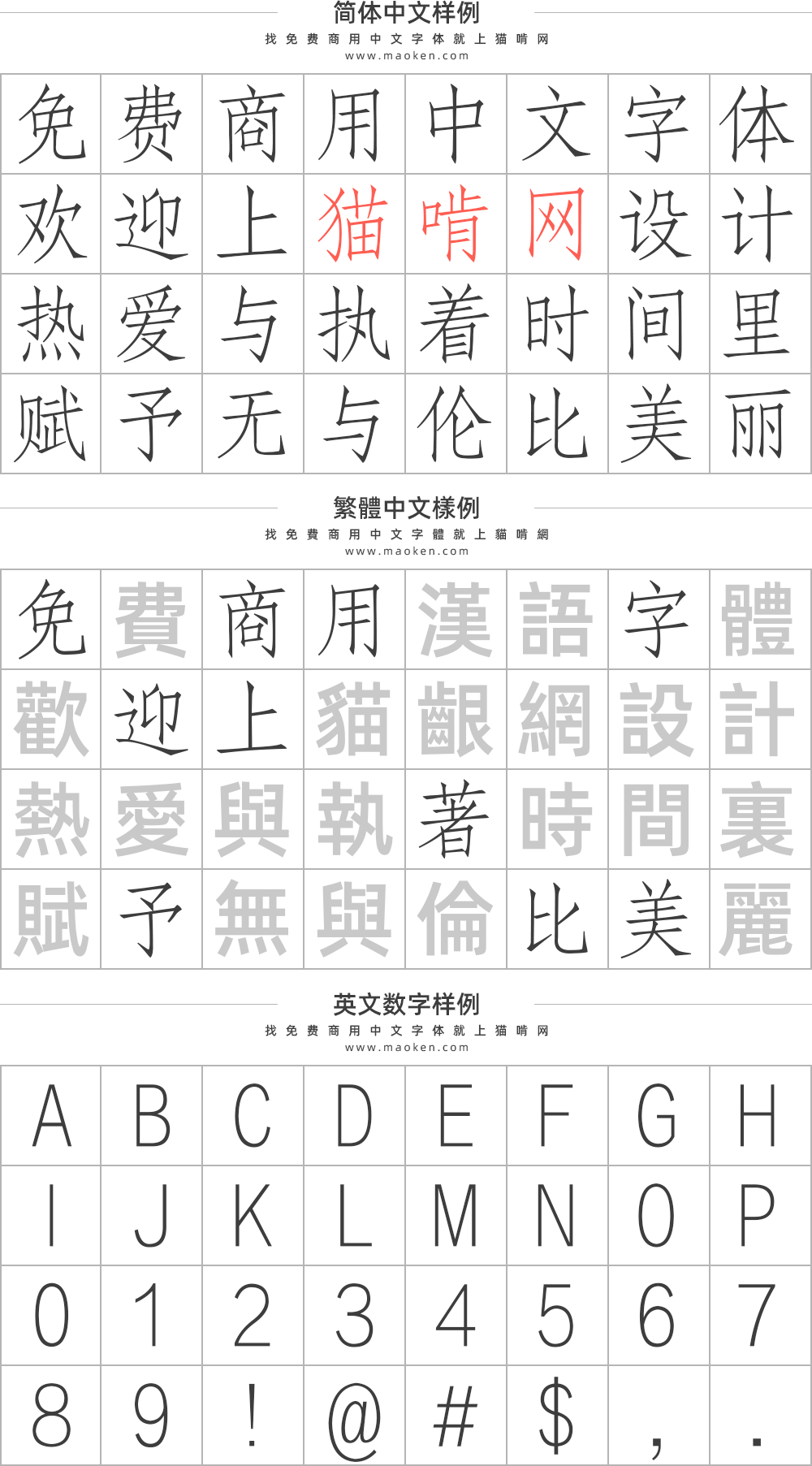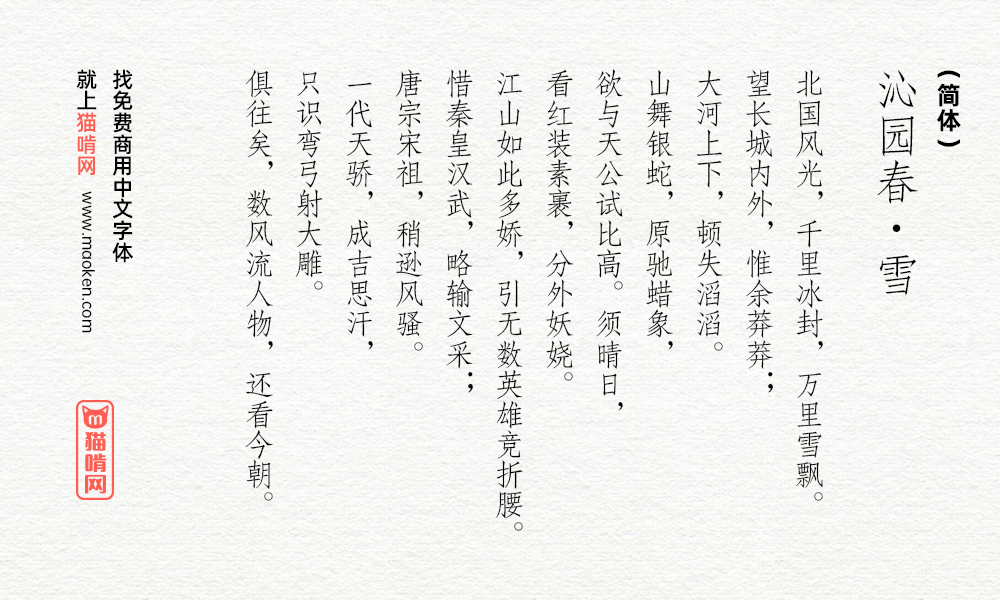
方正仿宋简体:方正字库送给大家免费商用的仿宋字体
说起方正字库,听到这个名号令各个设计师闻风丧胆。因为我们的第一印象是,糟了,是不是字体又侵权了?是不是又要被告了?但是,大家可能不知道,原来方正字库也有四款可以免费商用的字体,意不意外?惊不惊喜?这四款字体分别是「方正黑体」、「方正仿宋」、「方正楷体」、「方正书宋」。
字体特色
“仿宋体”产生于20世纪初,由当时的铅字制作者仿宋版书中的瘦细字体而制成。「方正仿宋」源于铅字时代的字稿,其字身略窄,笔画瘦硬,横竖笔画等粗,起笔处有斜势棱角,折笔处棱角分明,整体字形挺拔俊秀,给人以悦目之感。因清晰美观,容易辨认,长期被用于工程图纸文字和书刊中的引文。